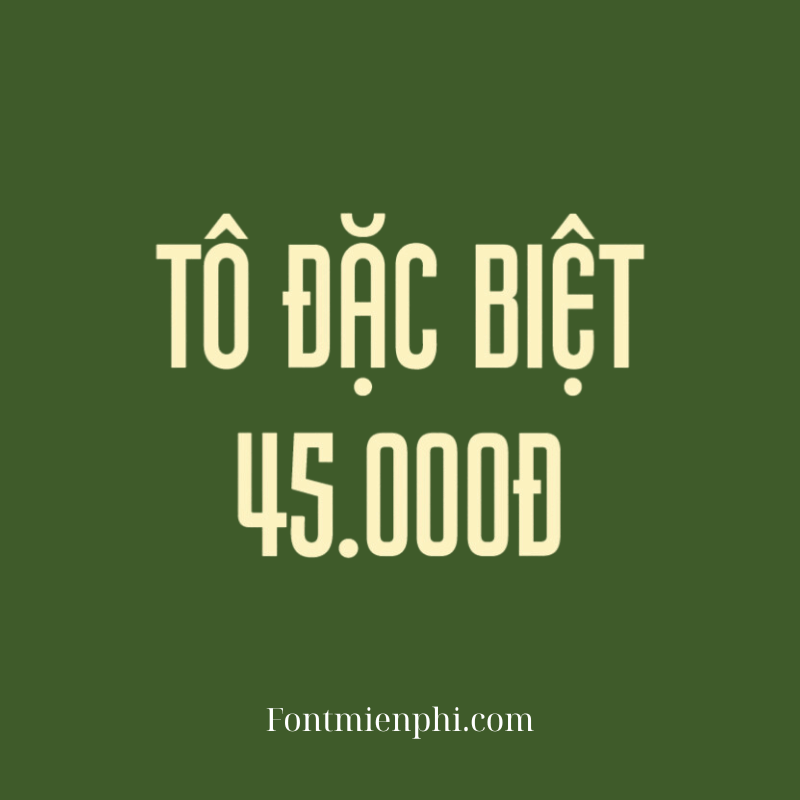
Font Việt hóa 1FTV VIP Pretender
Font Việt Hóa 1FTV VIP Pretender – Phong Cách Độc Đáo Cho Thiết Kế
Giới Thiệu
Font Việt hóa 1FTV VIP Pretender là bộ font chữ nghệ thuật được thiết kế tỉ mỉ, hỗ trợ đầy đủ tiếng Việt, phù hợp cho các dự án sáng tạo. Với nét chữ cá tính và hiện đại, font chữ này giúp thiết kế của bạn trở nên ấn tượng và chuyên nghiệp hơn.
Đặc Điểm Nổi Bật
• Hỗ trợ tiếng Việt: Đầy đủ dấu và ký tự Unicode, tương thích với mọi phần mềm thiết kế.
• Phong cách độc đáo: Nét chữ mạnh mẽ, phù hợp với poster, logo, banner quảng cáo.
• Đa dạng ứng dụng: Dùng cho in ấn, thiết kế đồ họa, social media, game, và nhiều lĩnh vực khác.
Lợi Ích Khi Sử Dụng
Kết Luận